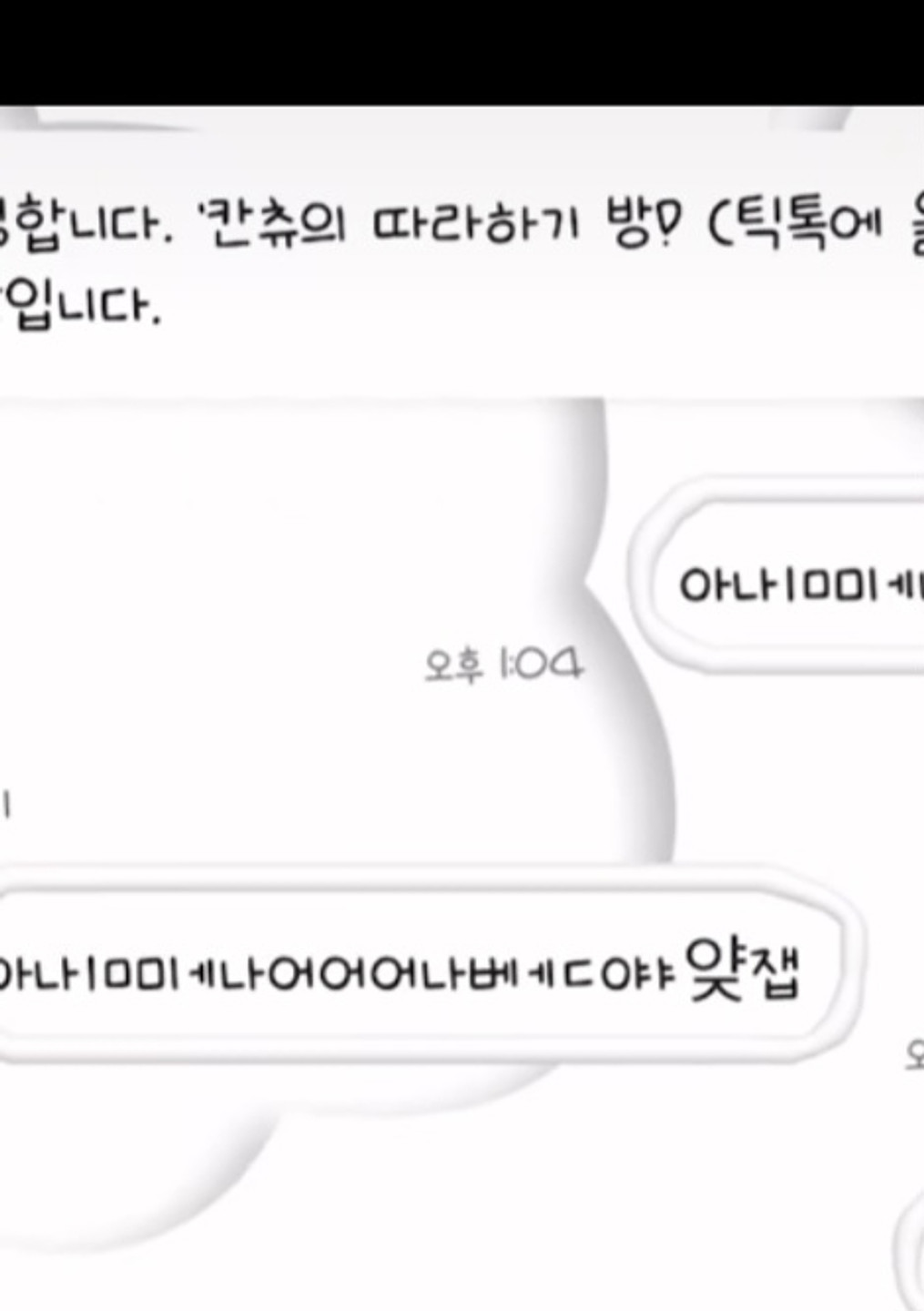
이 폰트가 뭘까요..?ㅠㅠ '수' '검' '실'이 특이한데 아무리 찾아도 동일한 폰트를 못찾겠어요.. ㅠ 일단 수박화체, 카페24 아네모네 에어가 비슷하긴 했습니다!
Saraknun 눈서리
이것도 약간 다르긴 한데 무료폰트를 찾으신다면 수박화체보단 이거랑 좀더 비슷하네요.